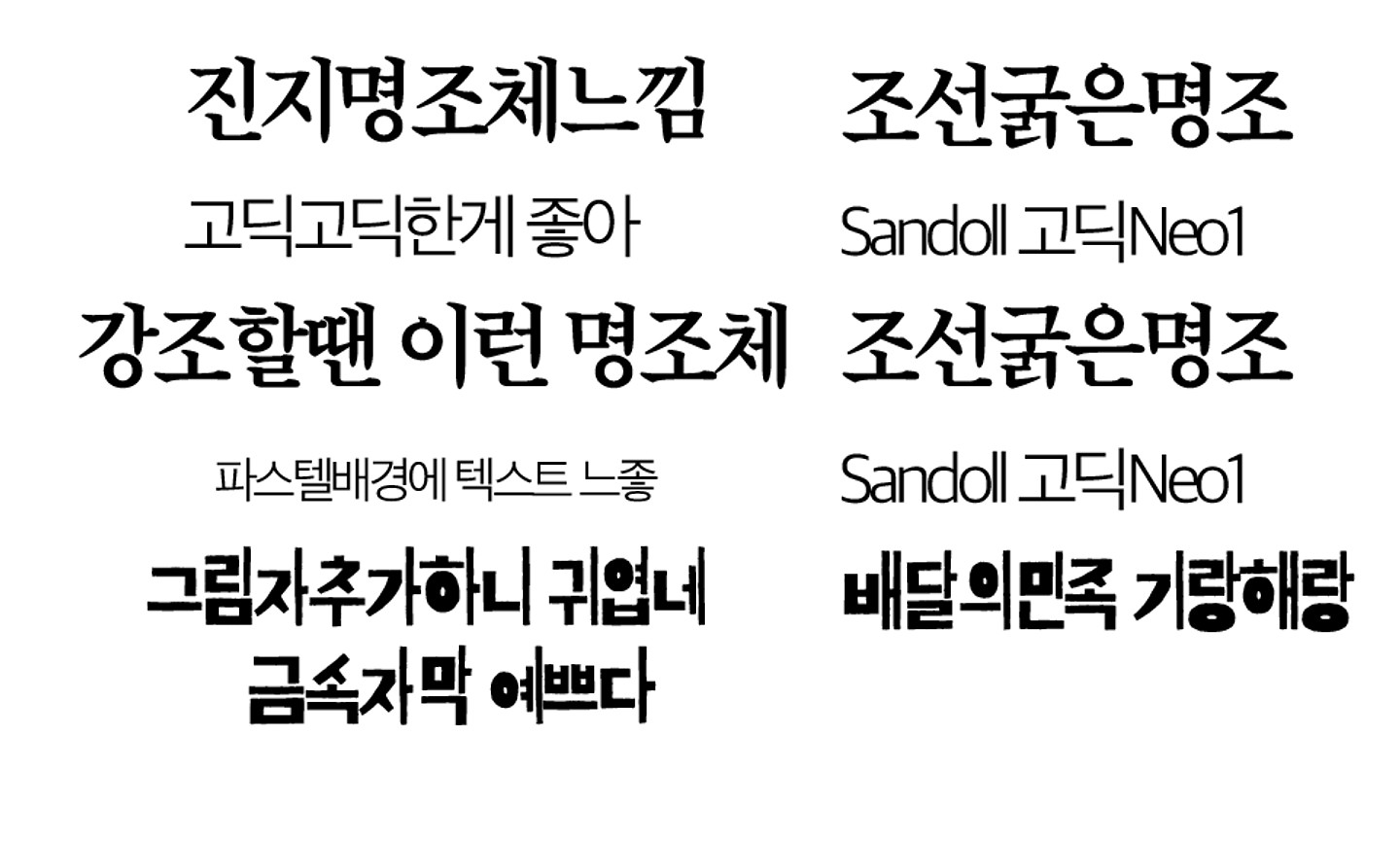
핀터레스트 감성,굵은테두리에 외곽테두리귀엽 이 폰트는 같은 폰트같은데 비슷한 픽셀폰트를 못 찾았어요ㅠㅠㅠ 픽셀폰트 무료 중에 갈무리 폰트 시리즈가 그나마 비슷하네요ㅠㅠㅠ 진지명조체느낌,강조할땐 이런 명조체 - 조선굵은명조(무료) 고딕고딕한게 좋아,파스텔배경에 텍스트 느좋 - 산돌 고딕 neo1(유료) 그림자추가하니 귀엽네, 금속자막 예쁘다 - 배달의민족 기랑해랑(무료) 폰트입니다!!